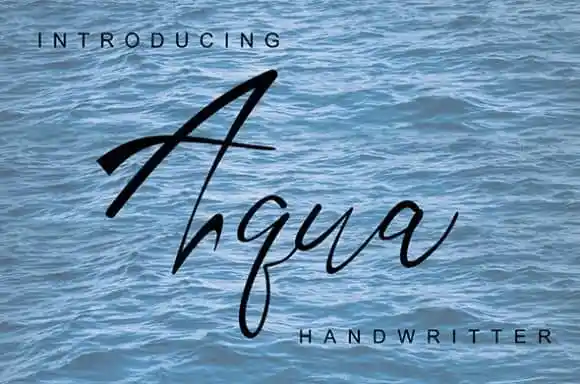
Aqua Script Font – Download Grátis
Aqua Script Font é uma elegante tipografia com um estilo casual que transmite autenticidade genuína. Desenhada por Andrean Prabowo e compartilhada através do site de desafios 99designs, esta fonte script encanta seus usuários com seu aspecto super-casual. Ideal para assinaturas de logotipos, postais, mídia social, convites de casamento, posts de blog e headlines, entre outros projetos gráficos. Seja você um designer ou um amante da arte digital, Aqua Script Font garante uma aparência personalizada em qualquer projeto que desejem criar.